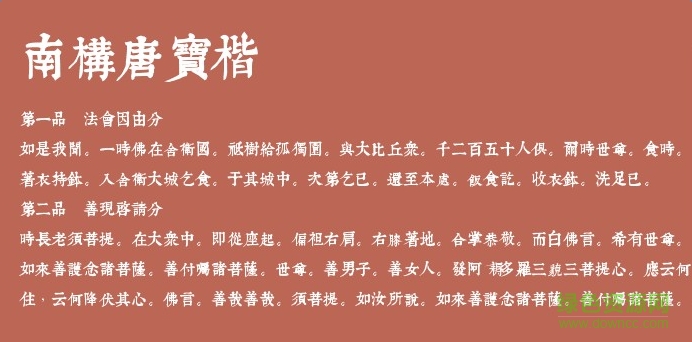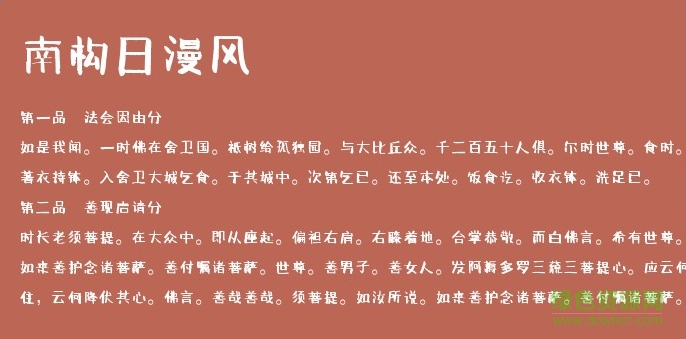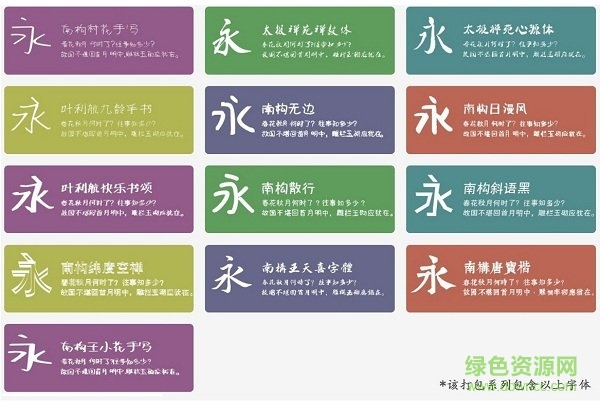
南構(gòu)字體系列打包是一款匯聚了葉根友旗下南構(gòu)字庫(kù)所有字體的合集,方便用戶更好的調(diào)用喜歡的手寫(xiě)體,給你的藝術(shù)設(shè)計(jì)帶來(lái)更多個(gè)人魅力,綠色資源網(wǎng)誠(chéng)意推薦!
南構(gòu)唐寶楷字體
南構(gòu)村花手寫(xiě)字體
南構(gòu)王小花手寫(xiě)體
南構(gòu)日漫風(fēng)字體
南構(gòu)王天喜字體
南構(gòu)圓點(diǎn)視線字體
南構(gòu)散行字體
南構(gòu)花韻字體
南構(gòu)王天喜行書(shū)簡(jiǎn)
葉根友南構(gòu)緯度空禪字體
南構(gòu)無(wú)邊字體
南構(gòu)汪本友行書(shū)
南構(gòu)標(biāo)羽歌士字體
南構(gòu)東方品
南構(gòu)斜語(yǔ)黑字體